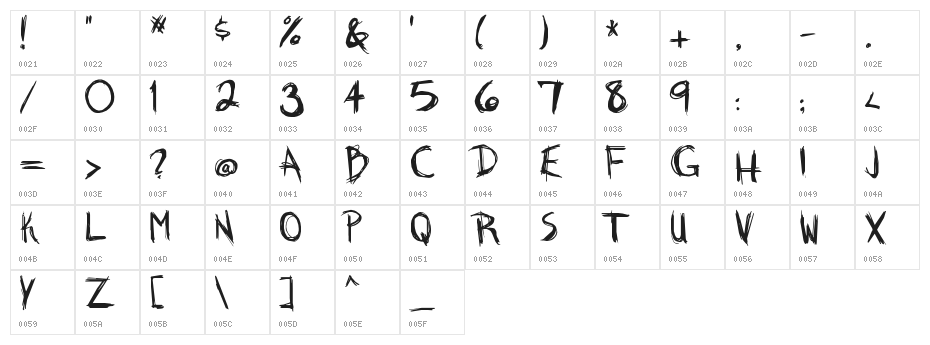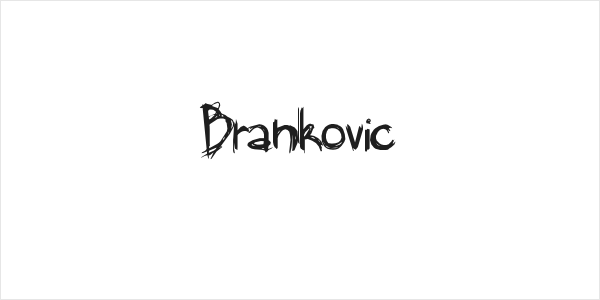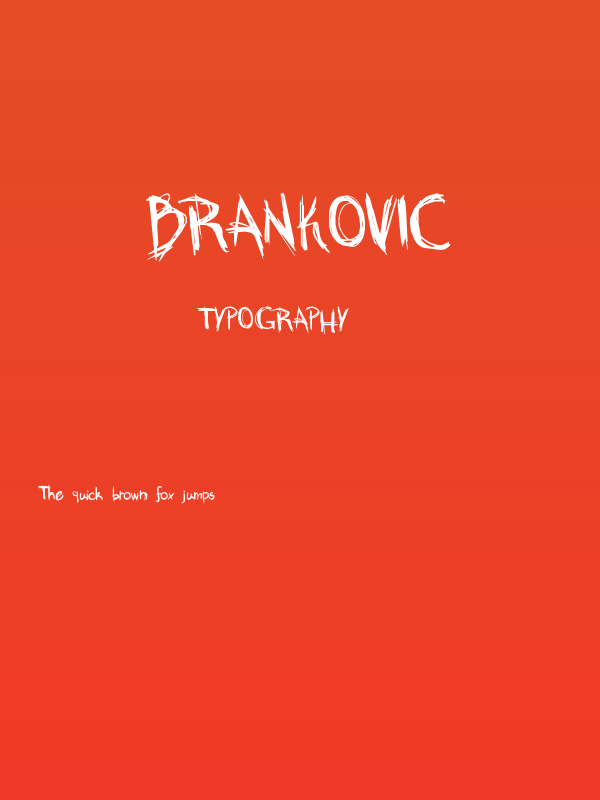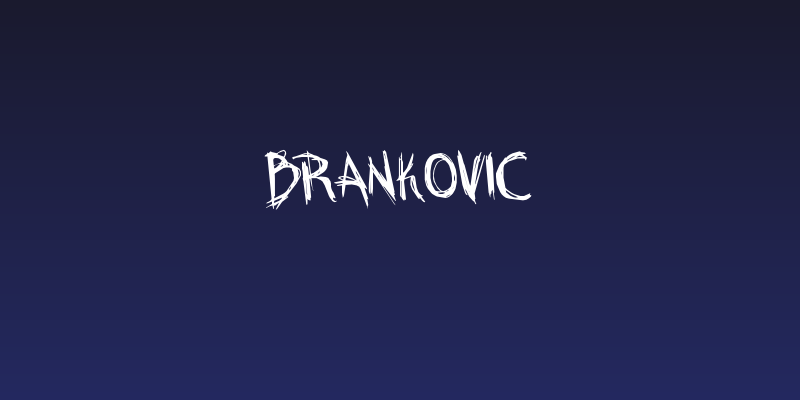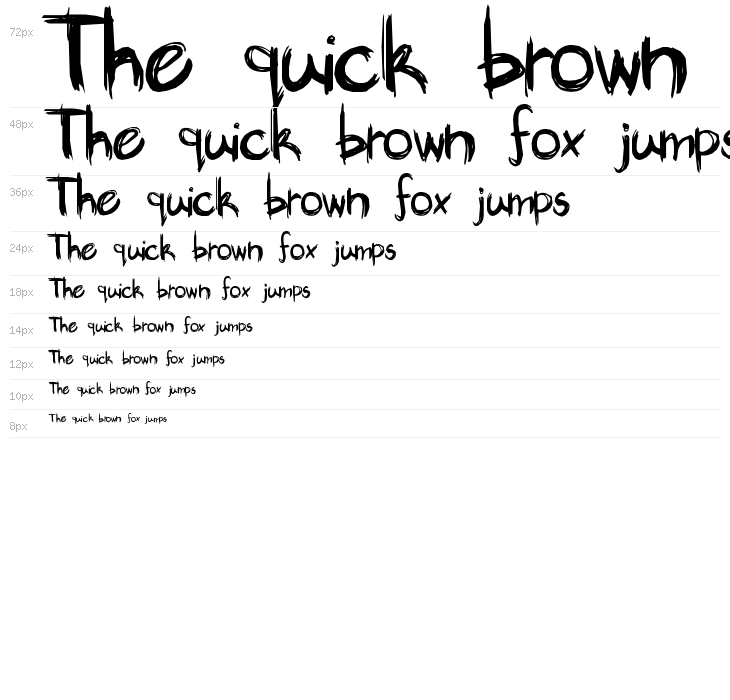
Brankovic Font
| النمط العام | Modern, Edgy |
| مشاريع مقترحة | Ideal for music album covers, edgy posters, graffiti art, and branding for alternative or punk-themed products. |